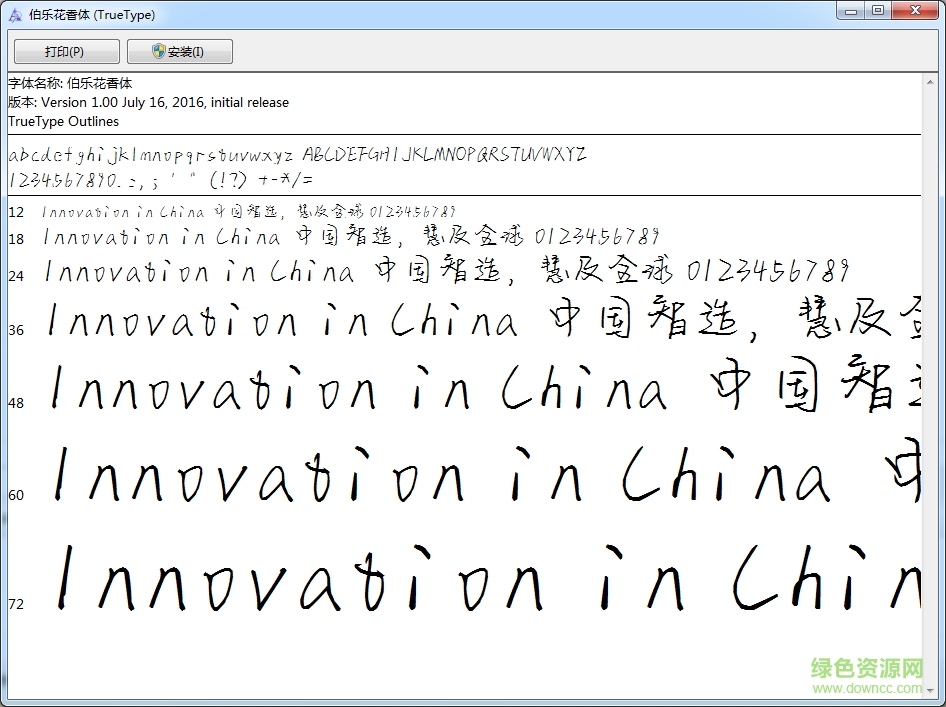
伯樂(lè)花香體是一款非常好看的字體,字體極具手寫(xiě)風(fēng)格,略帶潦草和奔放,整體偏細(xì),支持中文、英文和阿拉伯?dāng)?shù)字的輸入,可用于包裝設(shè)計(jì)行業(yè),歡迎有需要的朋友到綠色資源網(wǎng)下載使用!
潦草風(fēng)格的字體,適用于手寫(xiě)設(shè)計(jì),該字體線條非常細(xì)膩,字形飄逸大方,整體效果非常出眾,可以廣泛應(yīng)用于產(chǎn)品包裝、電視臺(tái)廣告、電影、電視劇片頭以及內(nèi)容用字等領(lǐng)域